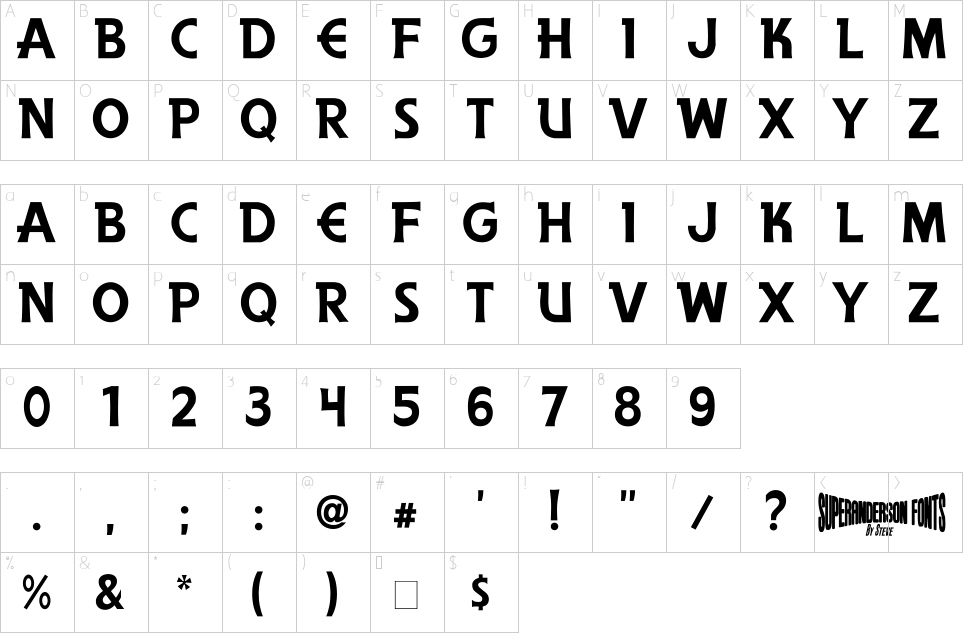
A fonte ‘Anderson The Secret Service’ é um design minimalista e elegante, ideal para ambientes gráficos contemporâneos e sofisticados. Desenvolvida por Steve Ferrera, esta fonte é uma escolha perfeita para quem procura uma opção de texto com estilo, sem comprometer a simplicidade e facilidade de uso. Com seu design moderno, a ‘Anderson The Secret Service’ encaixa-se perfeitamente em projetos digitais, desde aplicativos até design gráfico, trazendo um toque de modernidade e sofisticação a qualquer projeto. Com uma versão disponível tanto para Windows quanto para Mac, é uma fonte que todos podem facilmente usar em suas produções digitais. A fonte foi baixada mais de 30 mil vezes, indicando sua popularidade e qualidade. Quebre o estereótipo e dê a sua produção um toque autêntico e moderno com a fonte ‘Anderson The Secret Service’.